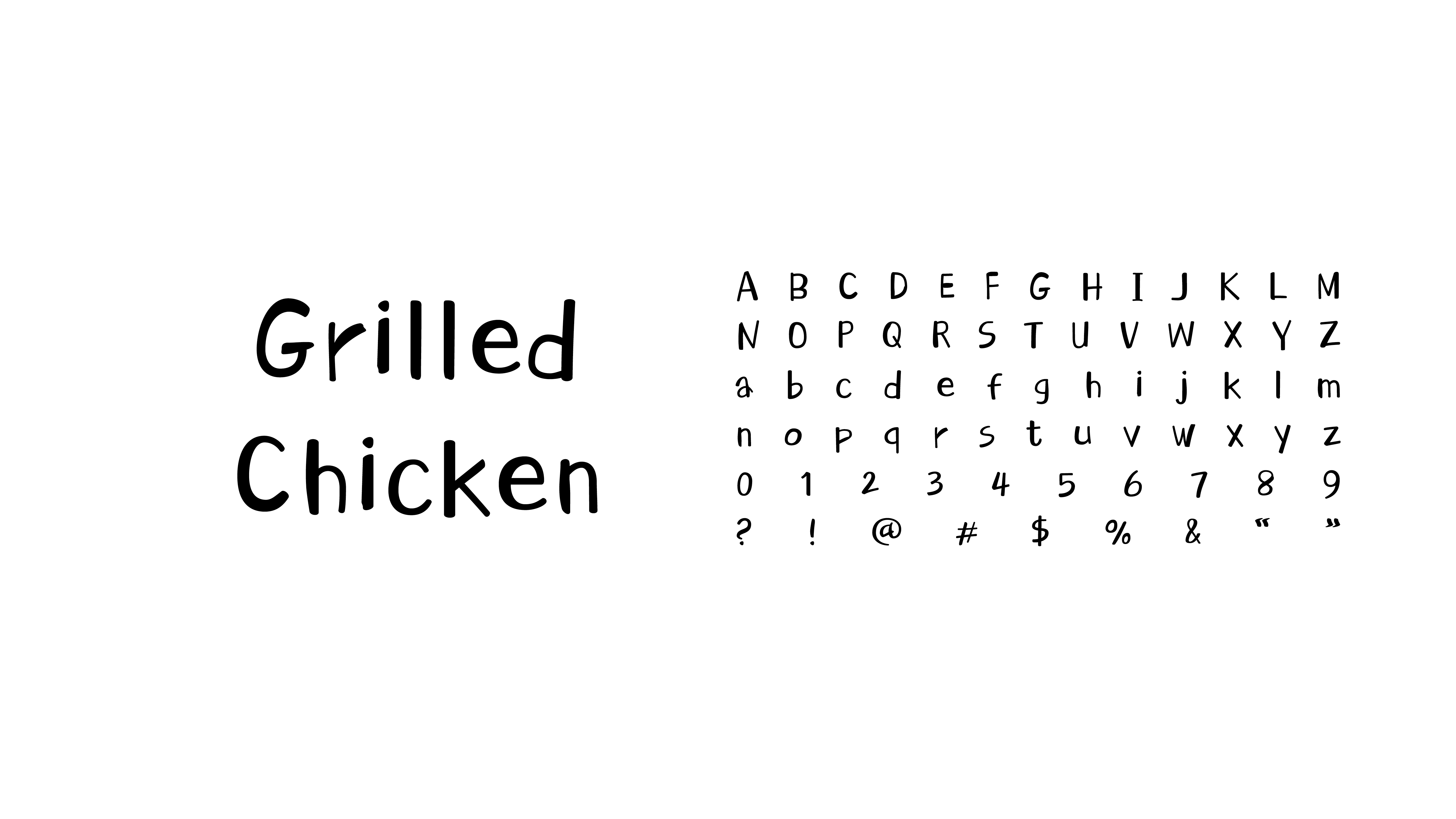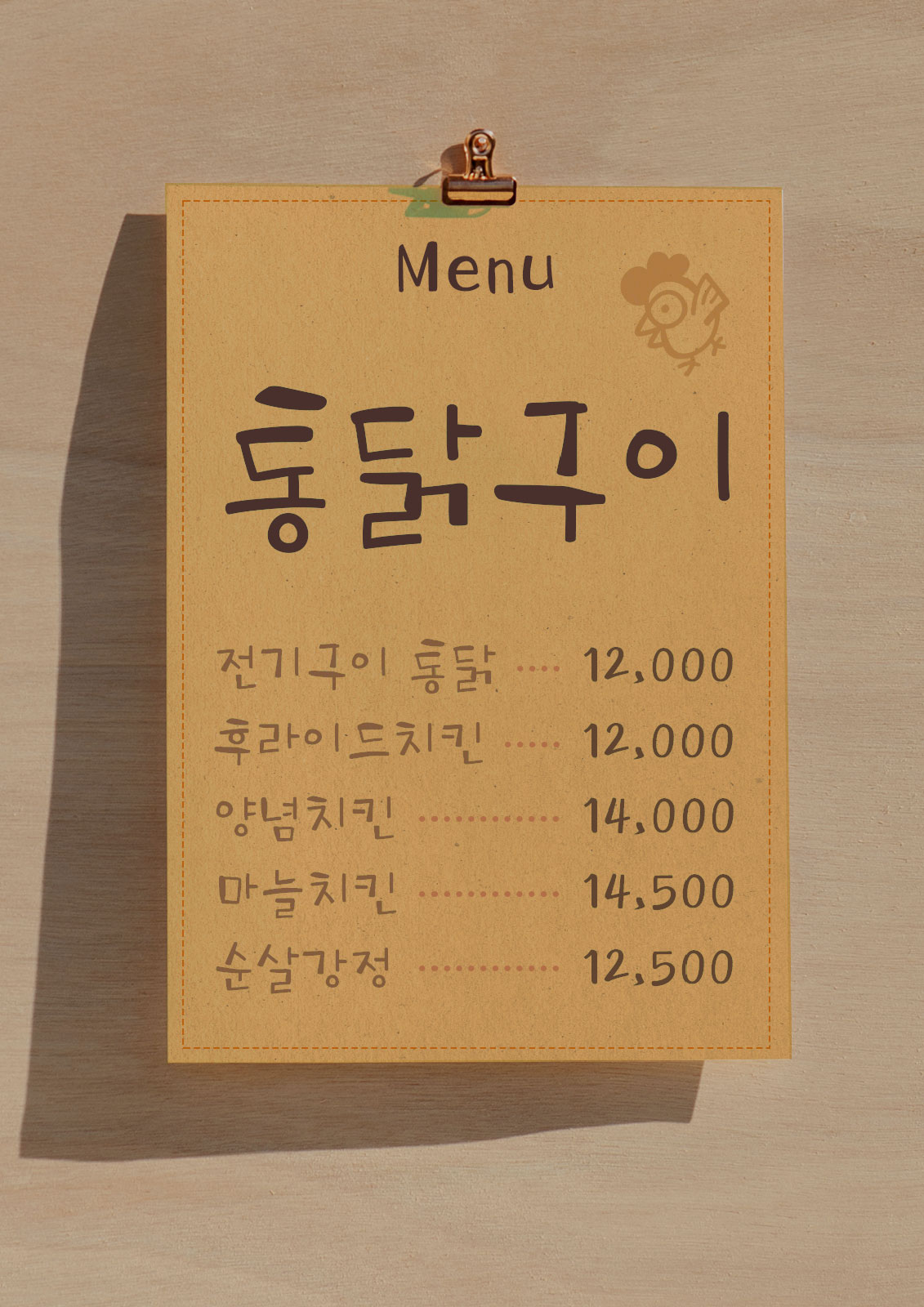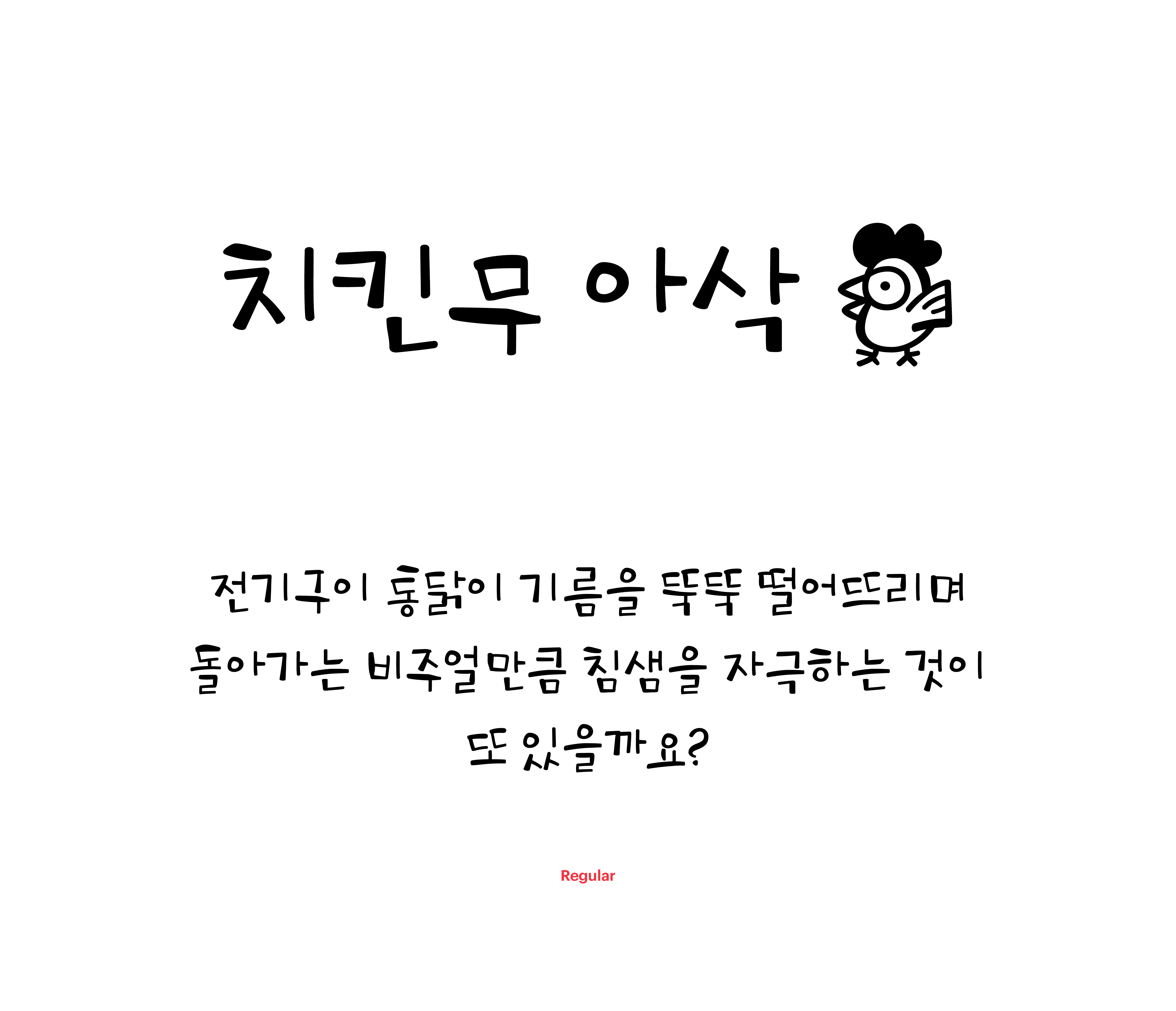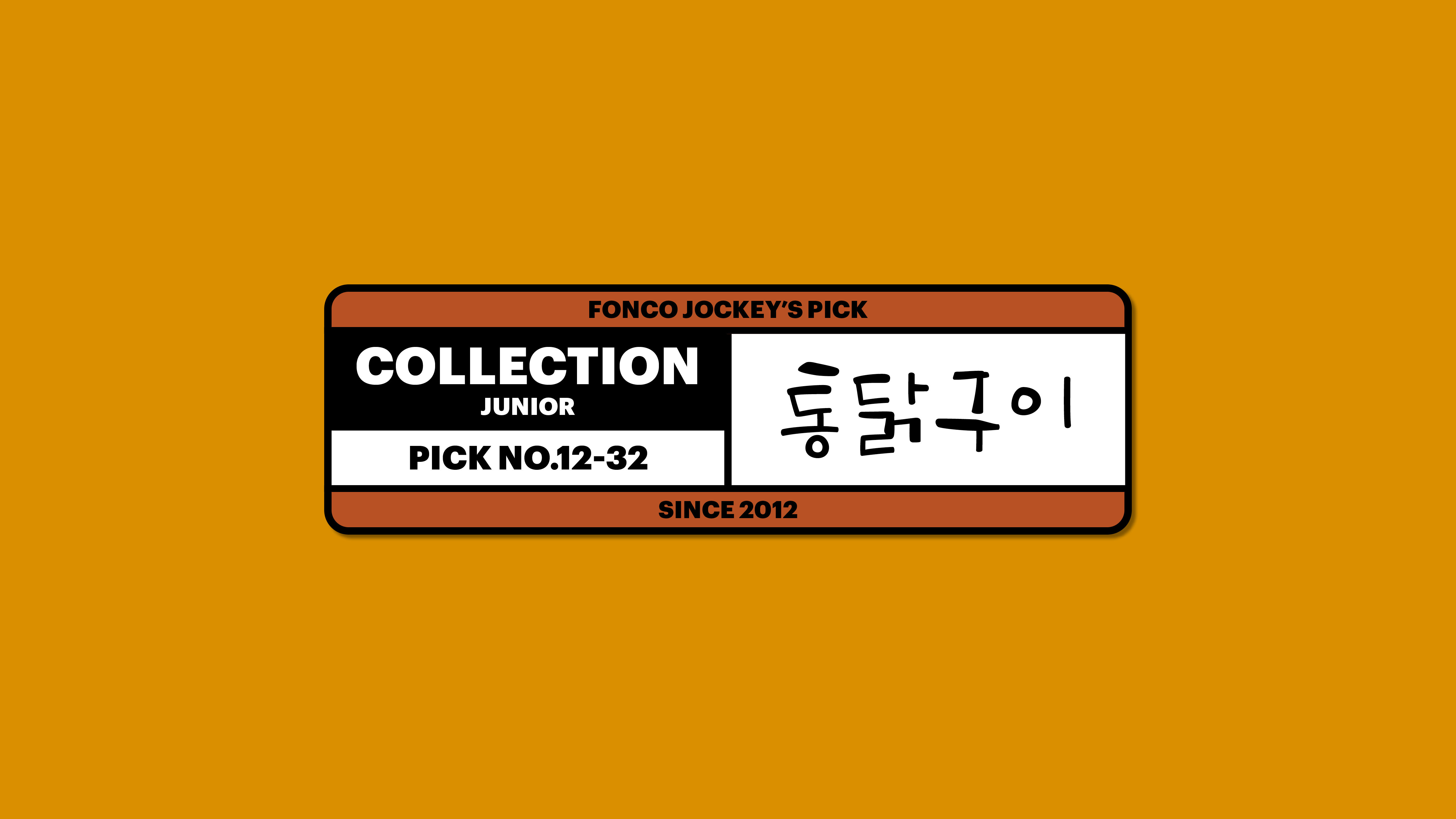
통닭구이
Yoon 통닭구이
전기구이 통닭이 기름을 뚝뚝 떨어뜨리며 돌아가는 비주얼만큼 침샘을 자극하는 것이 또 있을까요? 보기만 해도 고소한 냄새가 솔솔 풍겨오는 것 같은 이 울퉁불퉁한 폰트의 획을 좀 보세요. 하나를 뚝 뜯어서 머스터드 소스에 폭 찍어 맛보고 싶을 정도라니까요.